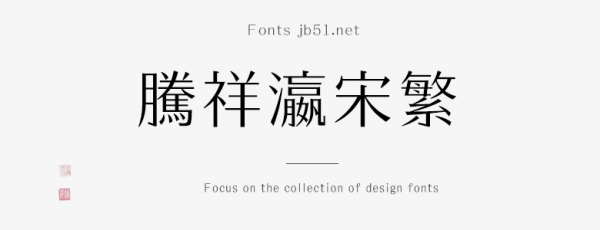
騰祥瀛宋繁W2是一款不錯的藝術(shù)字體,由騰祥字庫出品,這款字體結(jié)構(gòu)端正、重心平穩(wěn)、美觀實用,具有很好的視覺感,適合應用于藝術(shù)設(shè)計、平面宣傳設(shè)計、網(wǎng)頁設(shè)計,書法字帖等領(lǐng)域,需要的朋友可以前來本站下載。
字體介紹
此款字為騰祥瀛宋系列字庫,是騰祥公司自主精心設(shè)計開發(fā)的正文字體。一共有10款粗細,以期滿足用戶不同領(lǐng)域的用字需求。此款字為瀛宋W2,可用于正文、小標題等。整個系列字庫風格完全一致,不管是常用字或是非常用字,字字精美、結(jié)構(gòu)端正、重心平穩(wěn)、美觀實用。此款字為騰祥公司推送《2019森澤字體大賽》參賽作品。